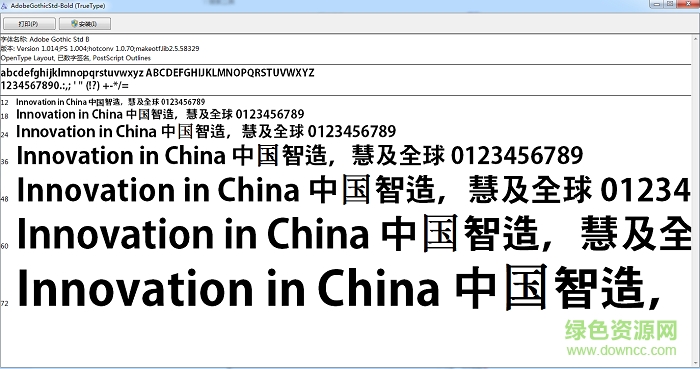
adobegothicstdbold.otf字體是一款粗體字體,字型飽滿,莊重大方,和黑體字體差不多,適合用在書刊、雜志的大標題或是海報宣傳字體上,比較醒目,需要的朋友快來下載吧!
它是根據(jù)企業(yè)或品牌的個性而設(shè)計的,對策劃的形態(tài)、粗細、字間的連接與配置,統(tǒng)一的造型等,都作了細致嚴謹?shù)囊?guī)劃,比普通字體相比更美觀,更具特色。
它運用夸張、明暗、增減筆劃形象、裝飾等手法,以豐富的想象力,重新構(gòu)成字形,既加強文字的特征,又豐富了標準字體的內(nèi)涵。